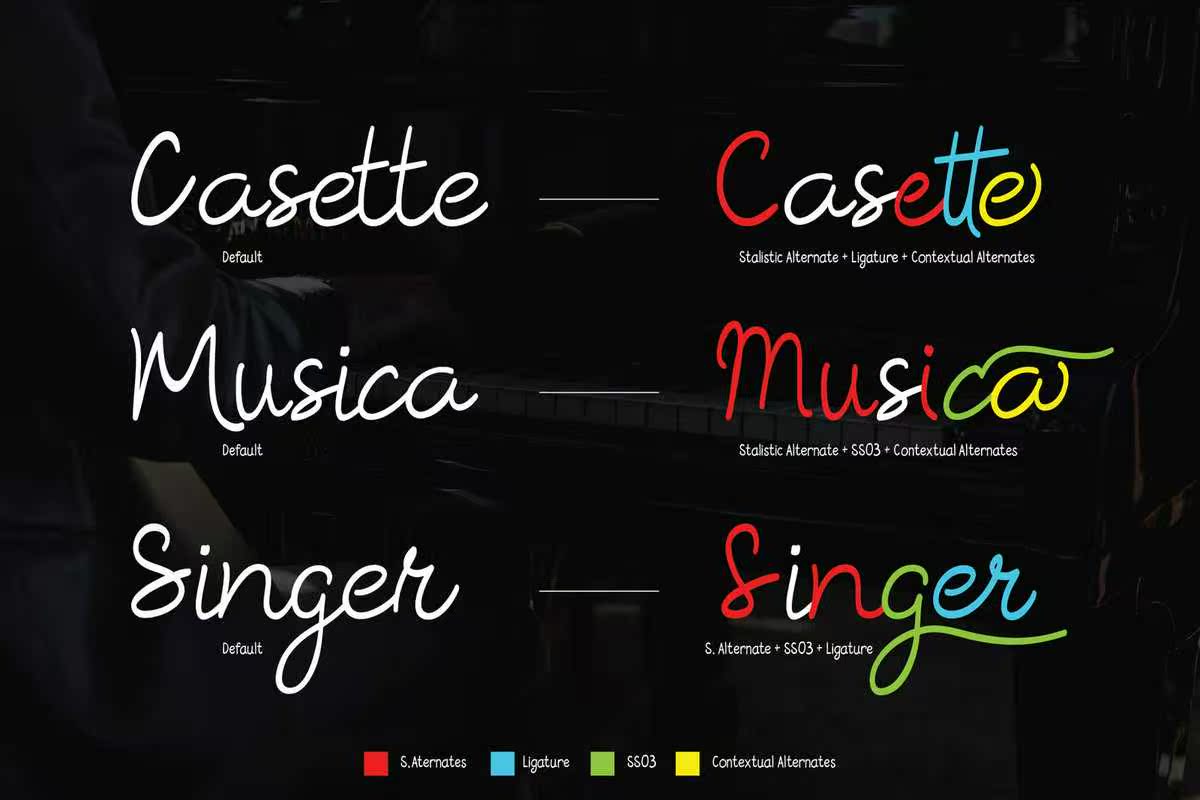
RosellaScript&Sans Font具有原始手写风格,外观自然美观。它适用于精品品牌、摄影、杂志、报价、名片、徽标、Poster等。字体有两种类型:Scriptsans、Scriptisequipped,具有开放式功能,如标准字体、连字、,上下文可选和多语言支持。RosellaScript&Sans字体具有原始手写风格,外观自然美观。适用于精品品牌、摄影、杂志、报价、名片、徽标、PosterAndMore。字体有两种类型:scriptandsans、ScriptIsequipped,具有开放式功能,包括基本的连字、连字、,上下文替换和多语言支持。